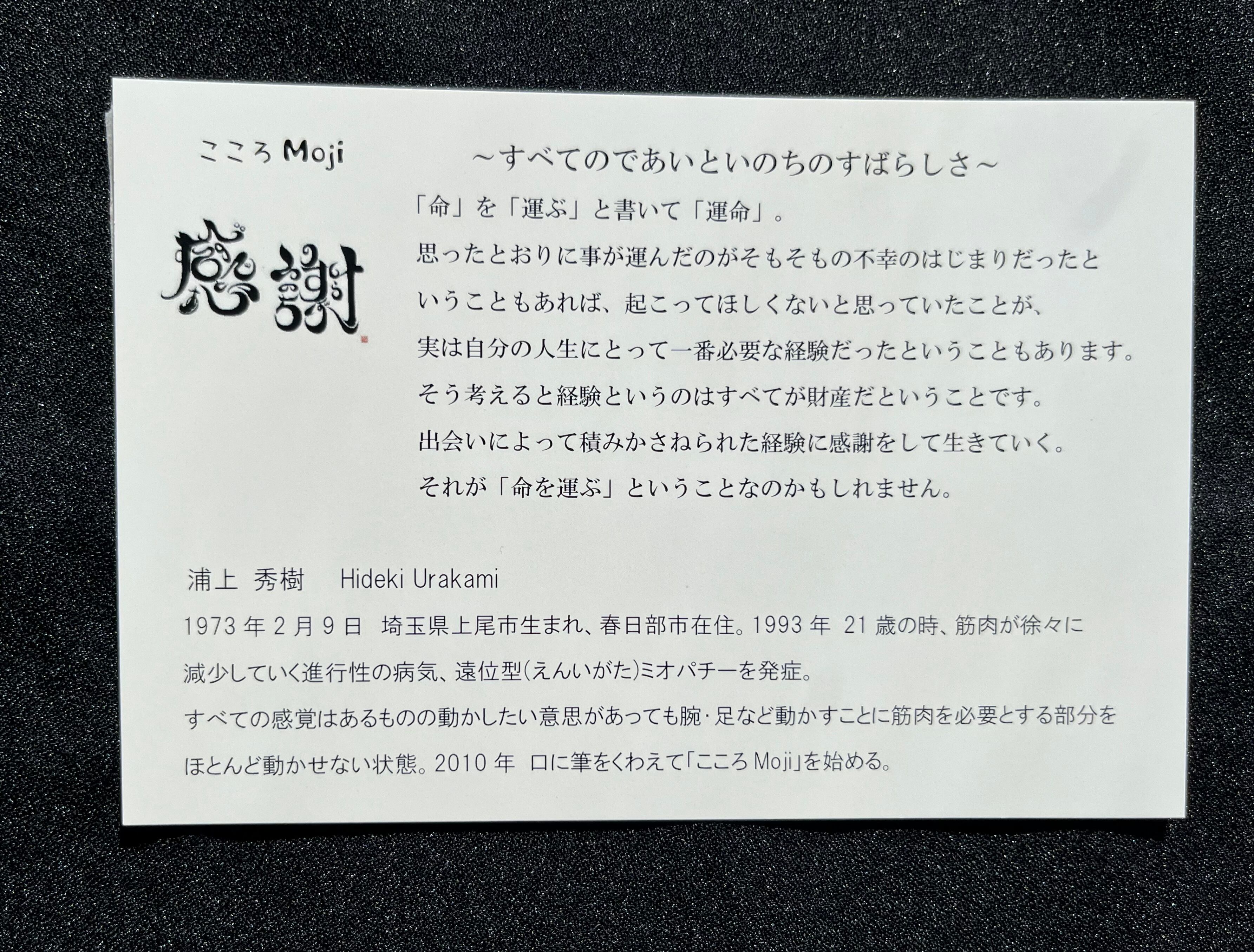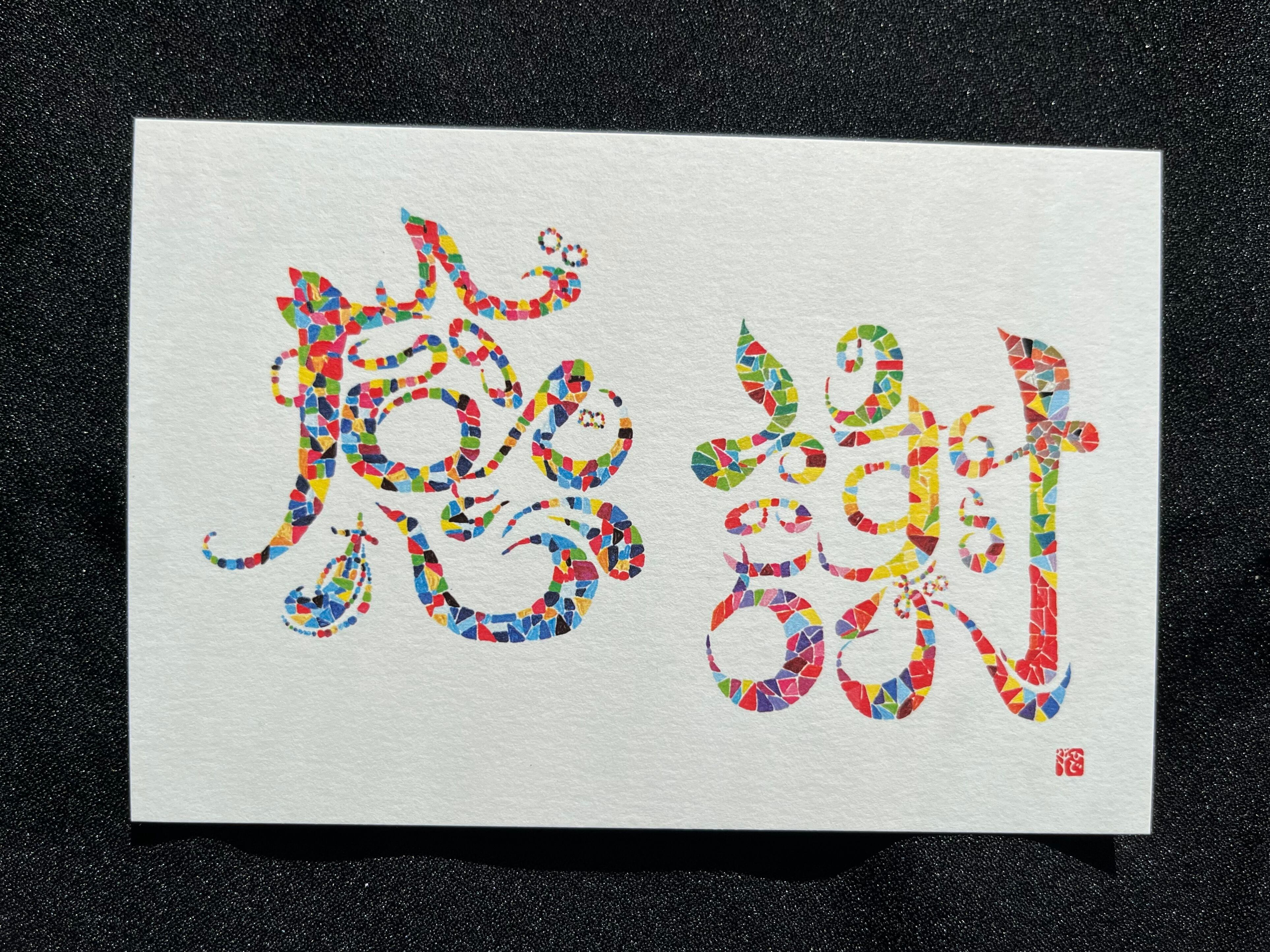
『感謝』~すべてのであいといのちのすばらしさ~(モザイクタイル風)
【解説】
「命」を「運ぶ」と書いて「運命」。
思ったとおりに事が運んだのが
そもそもの不幸のはじまりだったということもあれば、
起こってほしくないと思っていたことが、
実は自分の人生にとって一番必要な経験だったということもあります。
そう考えると経験というのはすべてが財産だということです。
出会いによって積みかさねられた経験に感謝をして生きていく。
それが「命を運ぶ」ということなのかもしれません。